Как выбрать необычные и стильные шрифты для вашего дизайна: лучшие варианты
На этой странице вы найдете подборку интересных шрифтов, которые идеально подойдут для различных креативных проектов, от логотипов до веб-дизайна. Мы собрали лучшие примеры шрифтов, которые могут подчеркнуть стиль и индивидуальность вашего проекта. Также вас ждут полезные советы по их использованию и выбору, чтобы сделать ваш дизайн еще более привлекательным и профессиональным.
При выборе шрифта важно учитывать стиль проекта: для серьезных и деловых тем лучше использовать классические, строгие шрифты, а для креативных и молодежных — что-то более необычное и яркое.
Обратите внимание на читаемость шрифта: даже самый креативный шрифт должен оставаться разборчивым, особенно в крупных текстах.
Используйте не более двух-трех шрифтов в одном проекте, чтобы избежать перегрузки и сохранить гармонию.
Проверьте шрифты на разных устройствах и экранах — они могут выглядеть по-разному на мобильных и настольных компьютерах.
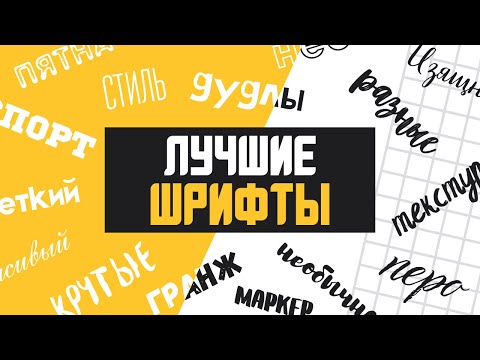
Если хотите, чтобы шрифт выглядел элегантно, выбирайте более тонкие линии, а для создания эффекта мощи — более жирные и массивные формы.
Не забывайте про контекст: шрифт должен поддерживать и усиливать сообщение вашего проекта, а не отвлекать внимание от его сути.
Для веб-дизайна используйте веб-шрифты, которые легко адаптируются под разные браузеры и устройства, чтобы избежать проблем с отображением.
Когда используете декоративные шрифты, старайтесь ограничиться заголовками и небольшими акцентами, чтобы не перегрузить текст.
Если ваш проект ориентирован на широкую аудиторию, выбирайте шрифты, которые будут одинаково хорошо восприниматься всеми пользователями.
Прежде чем окончательно утвердить шрифт, проведите тестирование на целевой аудитории, чтобы понять, как он воспринимается и воспринимается ли он с желаемым эффектом.